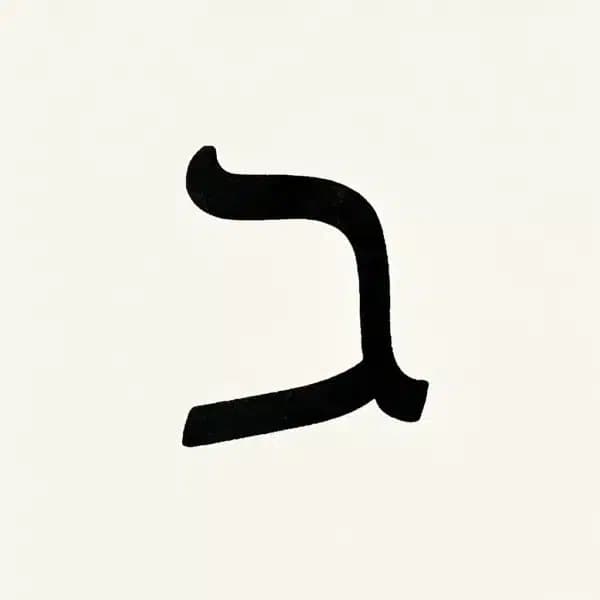
עולם העיצוב הדיגיטלי מציב בפני מעצבים ובעלי עסקים שאלות מורכבות בכל הנוגע לבחירת פונטים.
אחת השאלות המרכזיות היא האם פונטים חופשיים יכולים לשמש בפרויקטים מסחריים מבלי לפגוע באיכות או ליצור בעיות משפטיות.
התשובה אינה חד-משמעית, ודורשת הבנה מעמיקה של סוגי הרישיונות, איכות הפונטים והשימושים השונים שלהם בעולם העסקי.
בחירה מושכלת של פונטים יכולה לחסוך עוגמת נפש, כסף ובעיות זכויות יוצרים בהמשך הדרך.
חשוב לבדוק את מקור הפונט, את תנאי השימוש שלו, ואת ההתאמה שלו לשפה העברית ולמטרות העיצוביות של הפרויקט. כך ניתן ליהנות מעיצוב מקצועי, חוקי וייחודי גם בלי להתפשר על הסגנון.
המונח מתייחס לגופנים הזמינים ללא תשלום, אך לא כל פונט חינמי מתאים בהכרח לשימוש מסחרי.
ההבדל המהותי בין פונטים חינמיים למסחריים אינו נעוץ רק במחיר. פונטים מסחריים כוללים לרוב תמיכה טכנית, עדכונים שוטפים, ומשקלים ווריאציות נוספות.
עם זאת, גופנים חופשיים איכותיים כמו Roboto, Open Sans או Heebo מצליחים להציע רמת מקצועיות גבוהה ללא עלות.
בנוסף, פונטים חופשיים מאפשרים גמישות: ניתן לנסות פונטים שונים ללא התחייבות כספית, ולעיתים אף לערוך את הפונט בעצמכם אם הרישיון מאפשר זאת.
מצד שני, קיימים חסרונות משמעותיים. פונטים חופשיים הם נפוצים מאוד, מה שמקטין את הייחודיות של המותג שלכם.
פונט כמו Arial או Helvetica משמש במיליוני אתרים, וקשה לבלוט בעזרתו. בנוסף, פונטים בעברית זמינים פחות בגרסאות חינמיות איכותיות, ורבים מהם חסרים תווים מיוחדים או משקלים שונים.
בניגוד לאנגלית, בעברית יש פחות פונטים חופשיים איכותיים, וחלקם סובלים מבעיות טכניות כמו ריווח לא אחיד או תווים חלקיים.
הטיפוגרפיה התפתחות הכתב העברי חוקרת את השינויים בצורות האותיות לאורך הדורות, ידע חיוני למעצבי פונטים מודרניים.
הפיתוח של הכתב העברי הדיגיטלי נמצא מאחורי האנגלית בכעשור לפחות, ורק בשנים האחרונות החלו להופיע פונטים עבריים חופשיים ברמה מקצועית.
בעיה נוספת היא הצורך בפונטים בעברית עם ניקוד למסמכים חינוכיים או דתיים. רוב הפונטים החינמיים אינם כוללים ניקוד תקני, או שהניקוד לא מיושר כראוי עם האותיות.
זה יכול להוות בעיה משמעותית עבור לקוחות מתחומים ספציפיים.
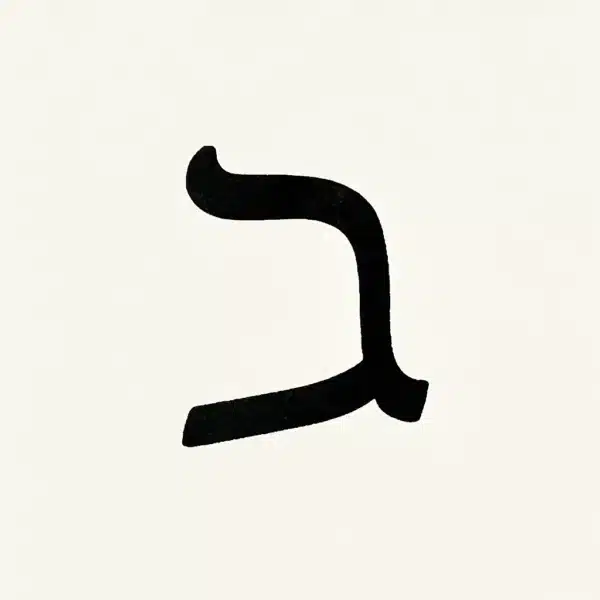
בחירת פונט מתאים דורשת התייחסות למספר קריטריונים:
בעידן הדיגיטלי, השימוש הנפוץ ביותר עם פונטים חופשיים הוא ביצירת תוכן לרשתות החברתיות. פונטים בסושיאל מדיה חייבים להיות קריאים גם בגדלים קטנים ובמסכי נייד.
פונטים כמו Rubik או Assistant מתאימים מצוין לעברית ברשתות, והם חופשיים לשימוש מסחרי.
למיתוג עסקי, פונטים ללא תשלום יכולים לשמש כפתרון זמני או לעסקים עם תקציב מוגבל, אך חשוב לזכור שהמיתוג שלכם יהיה פחות ייחודי.
עסקים המחפשים זהות חזקה, שקלו להשקיע לפחות בפונט אחד ייחודי למותג, ולהשתמש בחינמיים כמשלימים.
לסיכום, המפתח הוא לבחור נכון, לבדוק את תנאי הרישיון, ולהשתמש באופן אסטרטגי – למשל, לשלב פונט ייחודי מסחרי לכותרות עם פונט חופשי איכותי לגוף הטקסט. כך תקבלו את שני העולמות: ייחודיות וחיסכון.
פונטים חופשיים ניתנים להורדה ושימוש ללא תשלום, אך לרוב אין בהם תמיכה טכנית, עדכונים או מגוון משקלים. פונטים מסחריים, לעומתם, מגיעים עם אחריות, רישיון ברור וגרסאות רבות (Bold, Light וכו’).